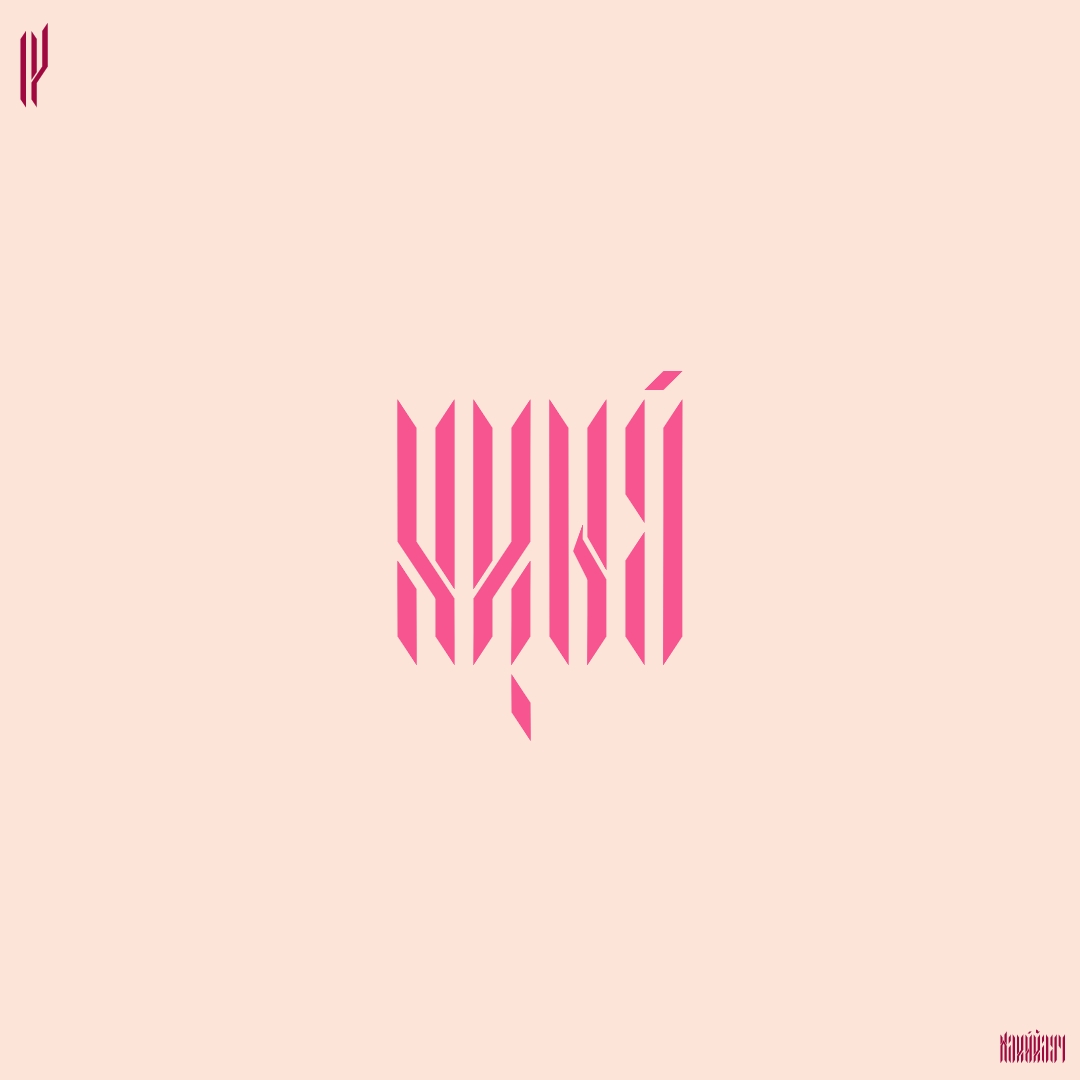
ฟอนต์ น้อยๆ
ฟอนต์น้อยๆ เป็น logo font ตัวอักษรน้อยๆ แนะนำไม่เกิน 5 ตัวอักษร เพราะตาเราจะเริ่มแยกแยะไม่ออกแล้ว
ชื่อฟอนต์ : น้อยๆ
ฟอนต์น้อยๆ เป็น logo font ตัวอักษรน้อยๆ แนะนำไม่เกิน 5 ตัวอักษร เพราะตาเราจะเริ่มแยกแยะไม่ออกแล้ว